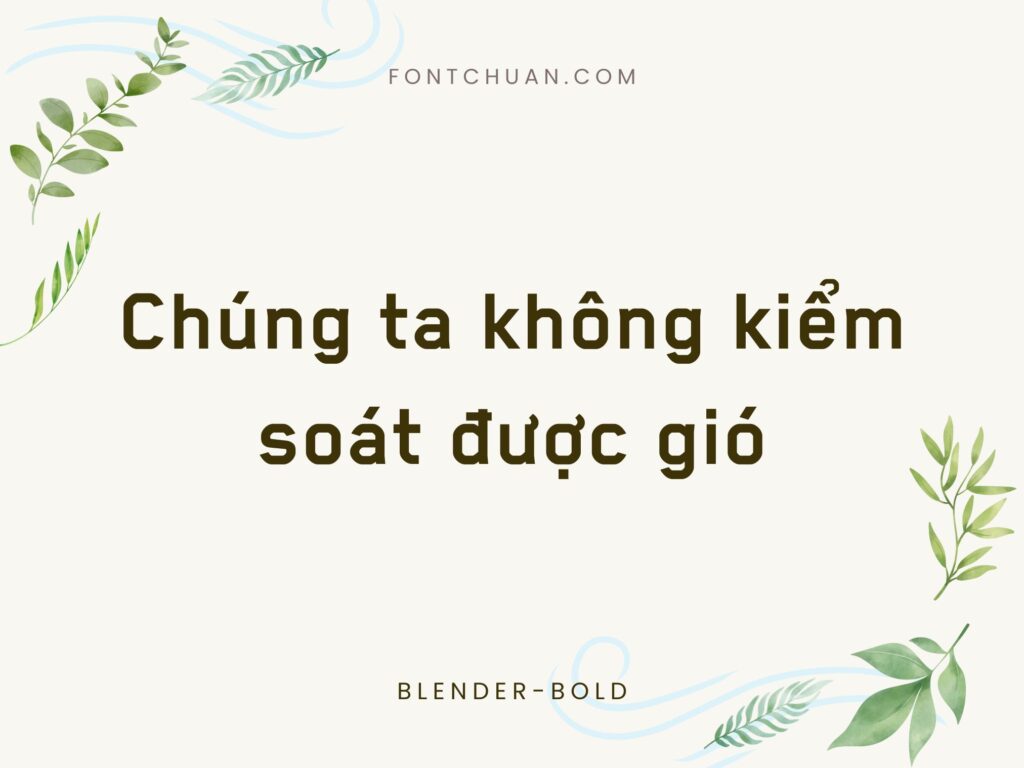
Blender-Bold là một Font chữ bất động sản hiện đại thuộc nhóm sans-serif, được thiết kế bởi Nik Thoenen và phát hành bởi Binnenland. Phông chữ này mang lại cảm giác chuyên nghiệp, mạnh mẽ và hiện đại — những yếu tố rất phù hợp trong các thiết kế liên quan đến thương hiệu doanh nghiệp, bảng hiệu và dự án bất động sản. Font chữ bất động sản Blender-Bold hỗ trợ đa ngôn ngữ, bao gồm tiếng Việt, Anh, Pháp, Tây Ban Nha, Đức và Ý, giúp người dùng dễ dàng ứng dụng trong nhiều dự án thiết kế khác nhau. Phông chữ này được thành viên Font Chuẩn sưu tầm và đăng tải nhằm phục vụ nhu cầu sáng tạo và ứng dụng thực tế của cộng đồng thiết kế.
Với thiết kế sans-serif hiện đại và tinh tế, Blender-Bold phù hợp cho các ứng dụng như thiết kế logo, tiêu đề, ấn phẩm quảng cáo và các tài liệu cần sự rõ ràng và chuyên nghiệp. Các ký tự có đường nét gọn gàng, độ dày đồng nhất, tạo cảm giác mạnh mẽ và dễ đọc cho văn bản. Trong lĩnh vực sự kiện, phông chữ này có thể được sử dụng trong các dịp như lễ hội, thiệp cưới và sinh nhật. Ngoài ra, Blender-Bold cũng thích hợp cho các ngành nghề như quảng cáo, giáo dục và công nghệ.